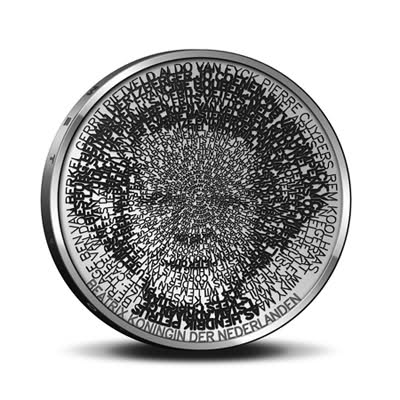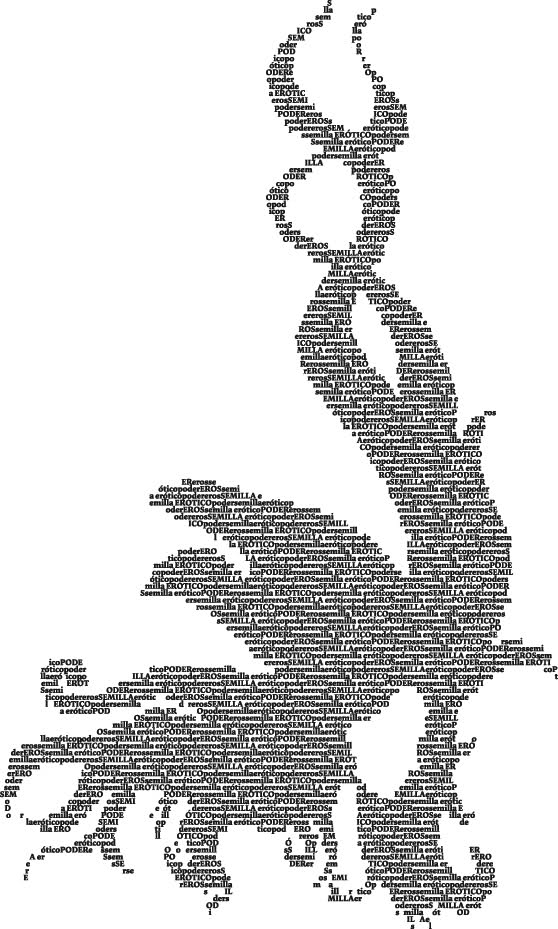
Freeware gesucht für Schrift-zu-Bild-Design
laut Zeitschriftenbeitrag wurde diese neue niederländische Euro-Münze mit einer - Zitat - Freeware aus dem Internet - designt. Kennt jemand von Euch ein Tool, das solche Ergebnisse "zaubern" kann? Mir sind bisher lediglich ASCII-Programme bekannt: http://www.typorganism.com/asciiomatic/- hier wird aber mit "echten" Schriften gespielt...
Automatisch ist das glaube ich aber auch da nicht möglich. Da fängt dann das Tüfteln jenseits von "ich hab da ein Programm runtergeladen" an.
Glaub ich auch nicht. Hier eine einfachere Version von Schrift zu Bild (mal abgesehen vom Qualitätsunterschied), da ich mir die Mühe nicht genommen habe, verschiedene Bildpartien mit unterschiedlichen Schnitten hervorzuheben (wie in deinem Bild). Alles Illustrator.
Sieht also eher nach Handarbeit aus - wäre ja auch zu schön gewesen, um wahr zu sein ;-)
Ich kenne bisher keine der genannten Freeware, werde mich aber mal dahinter klemmen.
Vielleicht geht das hier ja auch in die Richtung?
textorizer